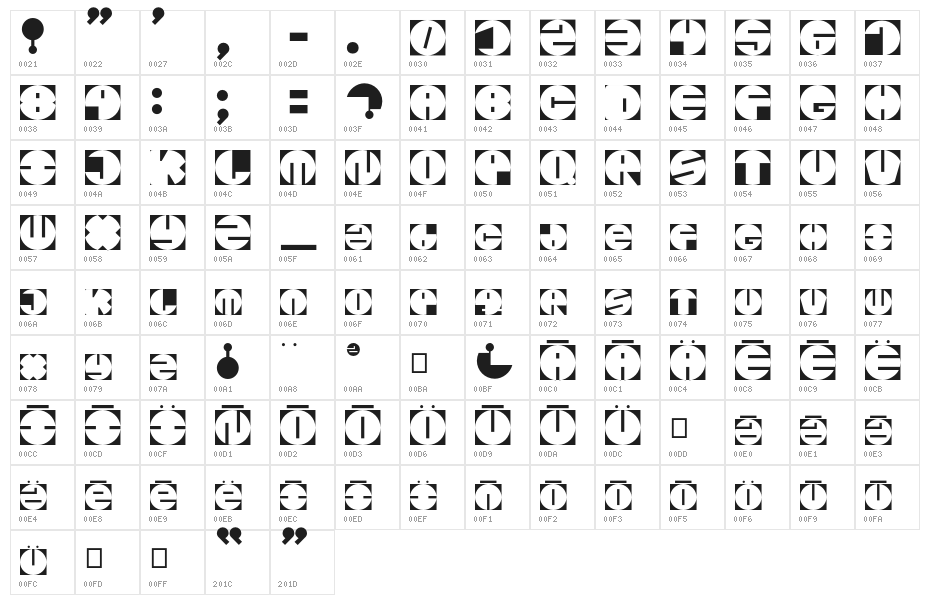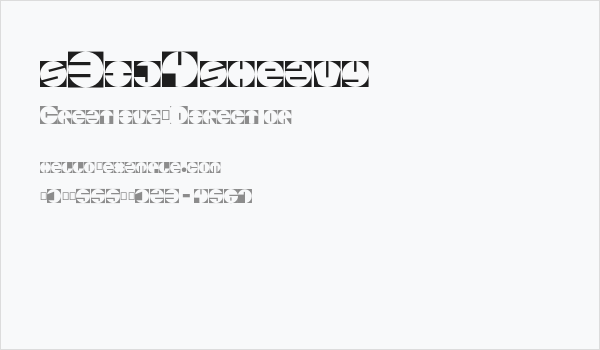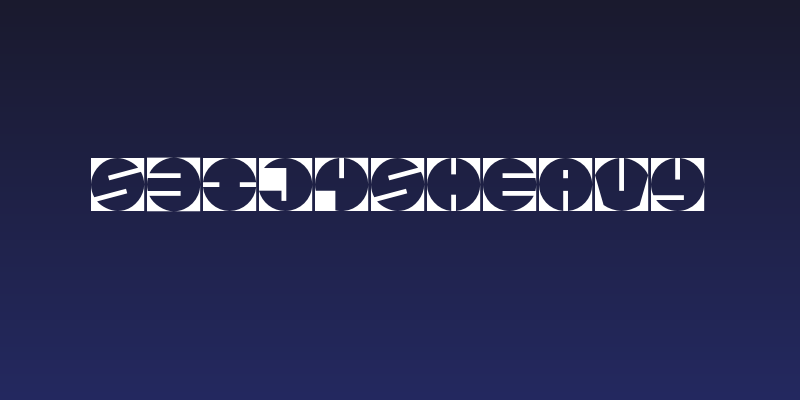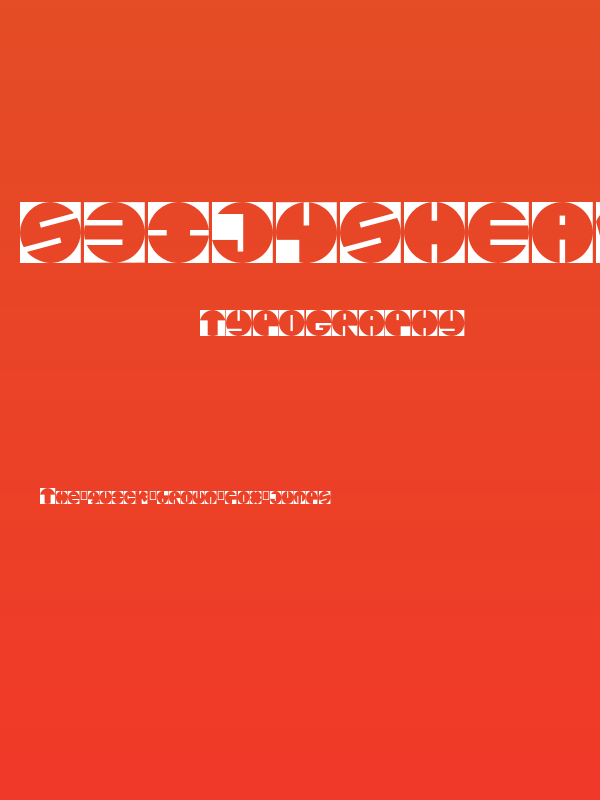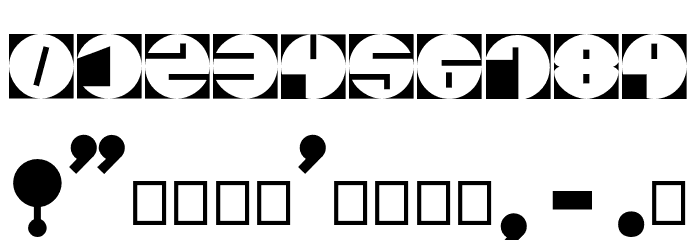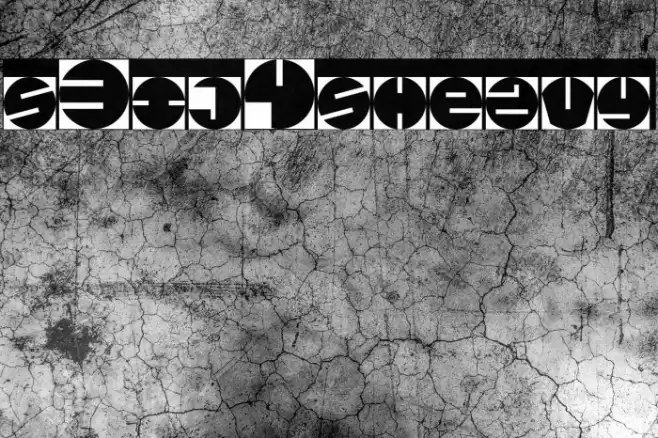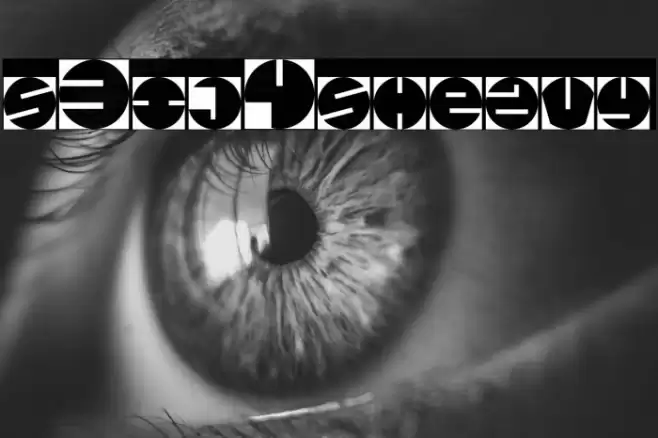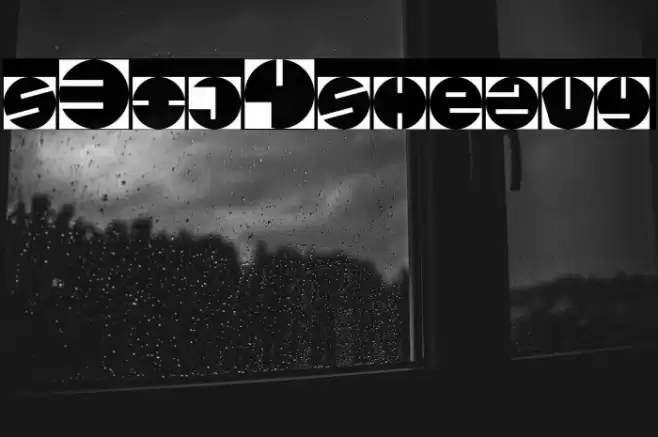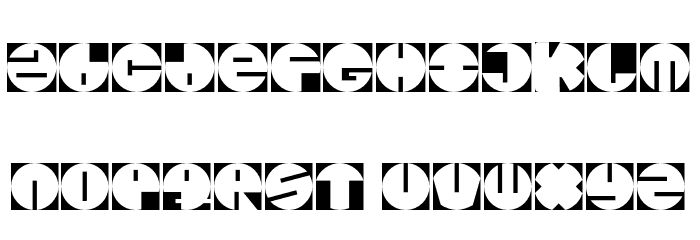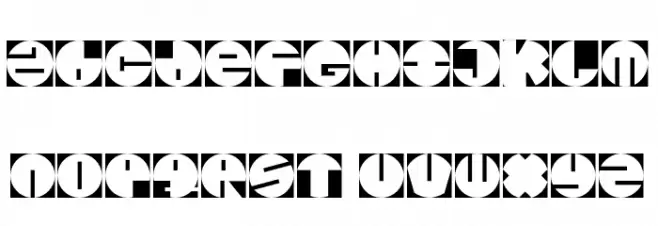
s3ij4sheavy Font
S3IJ4SHEAVY Litere mari
S3IJ4SHEAVY Litere mici
S3IJ4SHEAVY Alte caractere
| Proiecte propuse | Ideal for futuristic branding, tech-related projects, posters, and modern art installations. |